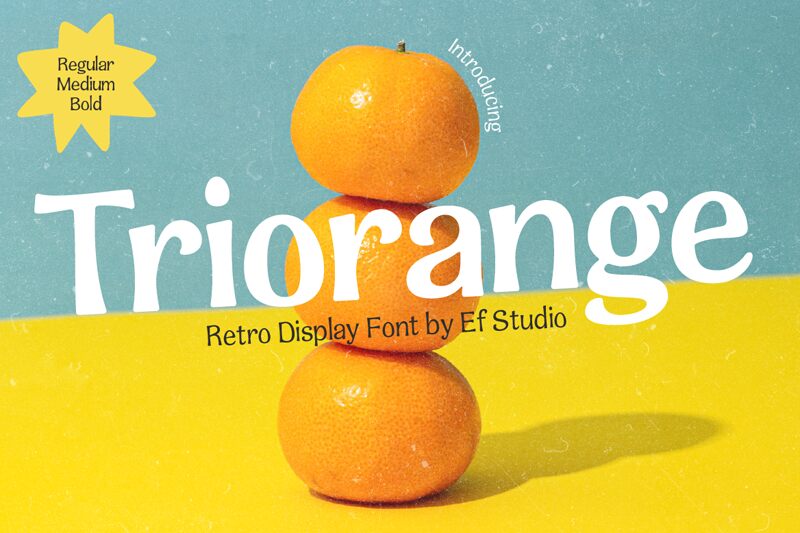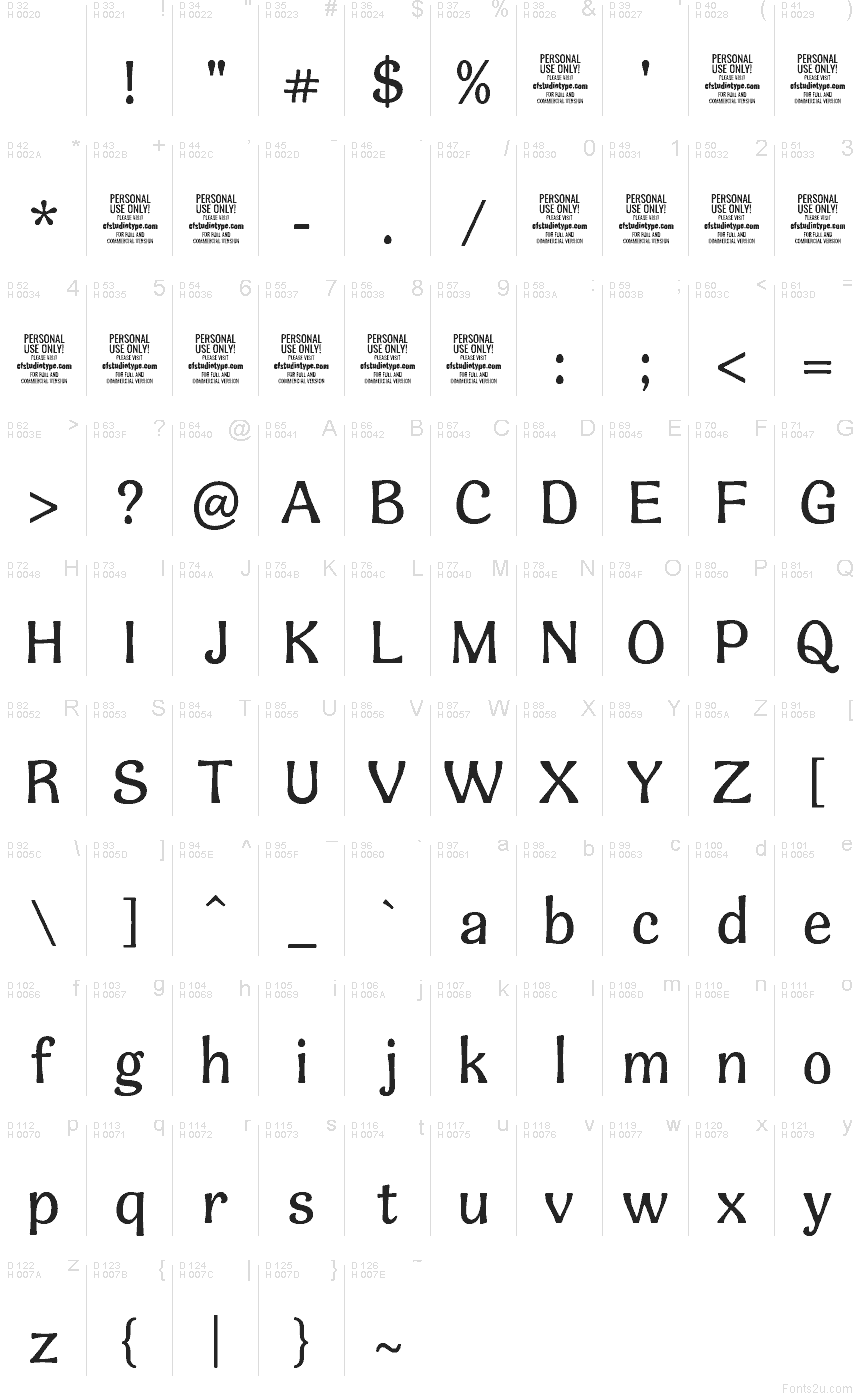
Triorange - Personal Use Medium
Triorange par Ef_Studio est une police d'affichage rétro gratuite aux traits doux et arrondis. Son style calligraphié confère aux lettres un rythme détendu et légèrement décalé. Les formes mêlent courbes fluides, quelques coupes asymétriques et un tracé généreux qui évite toute rigidité au design.
Triorange est idéale pour les titres d'affiches, les menus de café, le packaging, les logos, les flyers d'événements et les éléments éditoriaux nécessitant une touche chaleureuse et nostalgique. Cette police gratuite possède suffisamment de personnalité pour mettre en valeur de courtes phrases, tout en conservant une régularité parfaite pour vos besoins en image de marque, titres et visuels pour les réseaux sociaux.